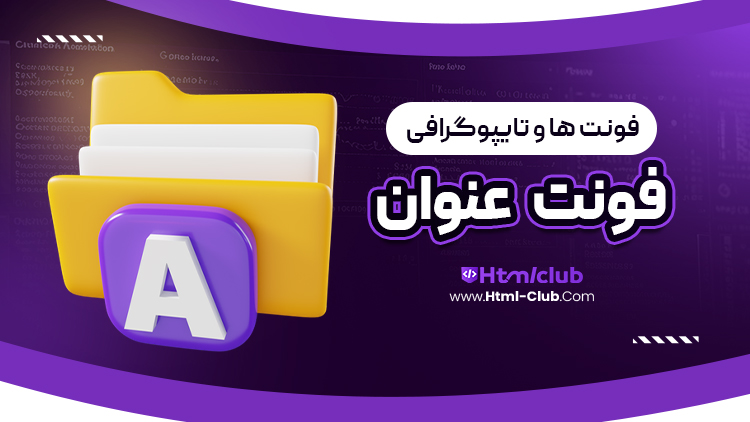
فونت عنوان در سایت html club برای شما عزیزان قرار داده شده است.فونت عنوان (یا فونت تیتر) یکی از عناصر مهم در طراحی گرافیک است که به طور خاص برای جلب توجه و ارائه اطلاعات کلیدی در متون مورد استفاده قرار می‌گیرد. این نوع فونت معمولاً در عناوین، سرصفحه‌ها، و بخش‌های مهم متون به کار می‌رود و نقش اساسی در ایجاد هویت بصری و جذب مخاطب دارد.
ویژگی‌های برجسته فونت عنوان:
نوآوری در طراحی
فونت‌های عنوان در انواع مختلفی از سبک‌ها و وزن‌ها موجود هستند. از فونت‌های مدرن و مینیمالیستی گرفته تا فونت‌های سنتی و تزئینی، طراحان می‌توانند با توجه به موضوع و هدف پروژه، بهترین گزینه را انتخاب کنند.
تنوع کاربرد
یکی از مهم‌ترین ویژگی‌های فونت عنوان، توانایی آن در جلب توجه مخاطب است. این فونت‌ها معمولاً بزرگتر و برجسته‌تر از سایر متن‌ها طراحی می‌شوند تا بتوانند نظر خواننده را به خود جلب کنند. پس میتوانید از این فونت در پوستر های  تبلیغاتی بنر ها و حتی دز سایت ها نیز استفاده کنید.
شخصیت منحصر به فرد
فونت عنوان می‌تواند به شکل‌گیری هویت بصری یک برند یا پروژه کمک کند. انتخاب یک فونت خاص و متمایز می‌تواند به یادآوری برند کمک کند و احساس منحصر به فرد بودن را به مخاطب منتقل کند.
پشتیبانی از زبان های مختلف
این فونت از تمام حروف زبان های فارسی و عربی به خوبی پشتیبانی میکند.